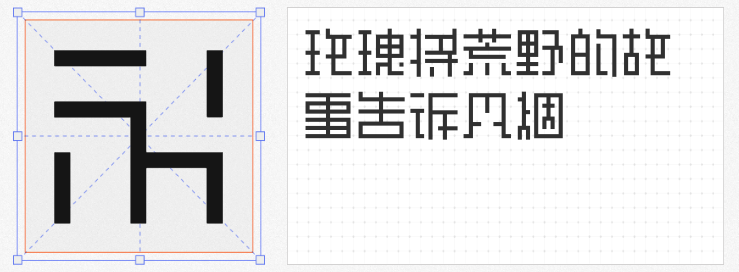
在商业设计领域,兼具创意与实用性的免费字体是提升作品竞争力的关键工具。以下四款风格迥异的免费商用字体,通过独特的设计逻辑与视觉语言,为界面设计、品牌传播、文化创作等场景提供高效解决方案。
这款类像素体以11×11像素为基准单位,通过点阵与横竖线的几何组合实现字形构建。其简化策略遵循「外围优先」原则——先保留部件轮廓(如「目」简化为「日」),再调整复合结构(如「吕」简化为上下两个「日」)。这种克制的设计既保留了汉字识别性,又赋予文字科技感与未来感,尤其适合游戏UI、数据可视化或科技品牌视觉系统。
作为专为数字界面优化的点阵字体,甜橙点阵体以7像素尺寸实现远超同类产品的清晰度。其方正的笔画结构与均匀的灰度分布,确保在小尺寸下仍具备良好可读性。经ZFONT修正后,字体名称、字高与ROS信息更规范,成为手游、软件工具或嵌入式系统的理想选择,既能传递信息,又能保持界面整洁。
这款字体通过圆润的笔画弧度与适度的墨迹飞白,还原了手写文字的生动质感。稚拙的连笔转折与Q弹的字符造型,在保持辨识度的同时,营造出童趣盎然的氛围。适用于儿童产品包装、教育类APP或社交媒体配图,其治愈系风格能有效拉近与用户的情感距离。
以行书为基底的一品启航体,通过昂扬的笔锋与舒展的结构传递进取精神。字体免费开放商业使用权,既可用于公益海报、文化展览等场景,也能为品牌标识注入文化底蕴。其刚柔并济的视觉语言,适合需要传递正能量或历史厚重感的设计项目。